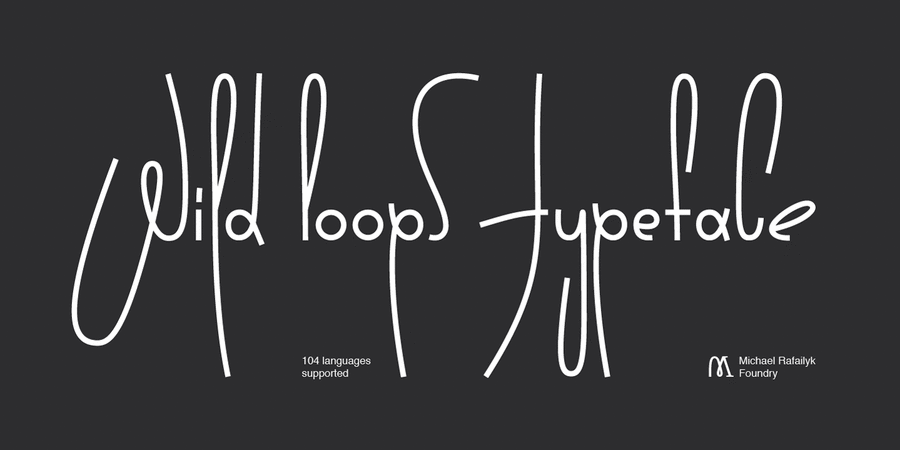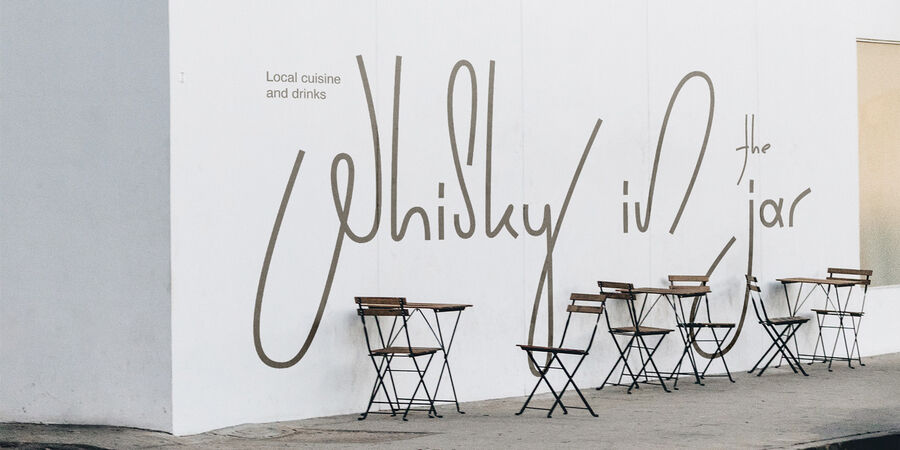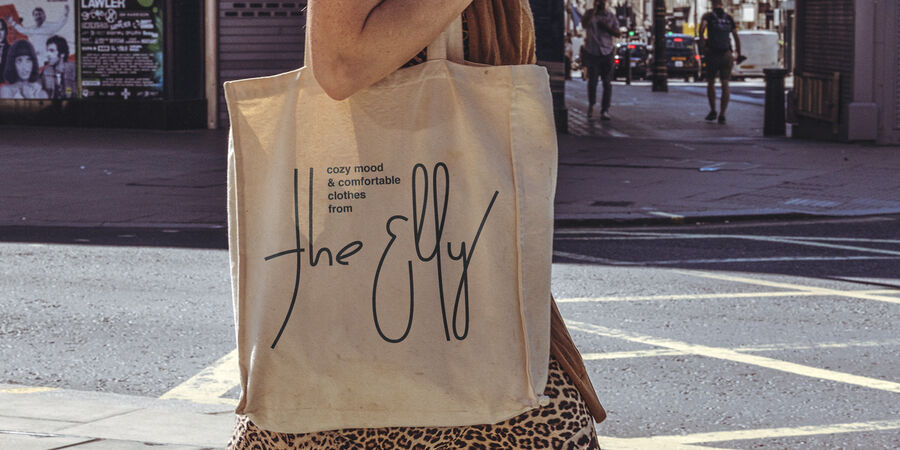
Wild Loops (2 шрифта)
Опис гарнітури Wild Loops — це дикий рукописний монолінійний шрифт для диких ідей. Натхненний маркерними ескізами та графіті на стінах, шрифт ідеально доповнює Doodle ілюстрації. Він розмовляє з молодою аудиторією і виглядає трохи божевільним із розтягнутими верхніми та нижніми виносними елементами. Головною особливістю шрифту є розумні контекстні альтернативи, які підставляють різні варіанти літер залежно від їх положення в слові (на початку, середині та в кінці слова), що робить написання більш рукописним.
OpenType features: Contextual Alternates, Stylistic Alternates, Ligatures, Superscript, Subscript.
Шрифт розробив Михайло Рафайлик у 2021 році.
Асоціації з сімейством шрифтів Wild LoopsОсобистість і характер гарнітури:
артистичний, динамічний, свіжий, веселий, легковажний, емоційний, лихий, рухливий, непосидючий, мультяшний, яскравий, смішний, добрий, милий, гнучкий, ручний, доброзичливий, зелений, грайливий, потішний, прикольний, живий, оригінальний, привітний, характерний, святковий, крафтовий, радісний, пустотливий, весняний, щасливий, стрибучий, танцюючий, моторний, вільний, розмашистий, модний, сміливий, цікавий, енергійний, самобутній, художній, мрійливий, виразний, творчий, активний, приємний, красивий, дитячий, наївний, пластичний, домашній, симпатичний, позитивний, кінематографічний, акуратний, нічний, дивний, молодіжний, експериментальний, музичний, дотепний, карикатурний, міський, вуличний, худий, стрункий, мотузковий, божевільний, пластмасовий, літній, темпераментний, помітний, екстравагантний, експресивний
хенд мейд, мультфільм, анімація, меблі, торгівля, кафе, бар, кіно, відпочинок, коктейль, кава, море, Інстаграм, графіка, ілюстрація, іграшка, ранок, весна, інтер'єр, квіти, подарунки, природа, розваги, живопис, косметика, краса, мода, одяг, танець, музика, ресторан, свято, виставка, селфі, мистецтво, світанок, пейзаж, гумор, дієта, Місто, театр, туризм, дитяча книжка, літо, захід сонця, вечір Гарнітура асоціюється з віком: